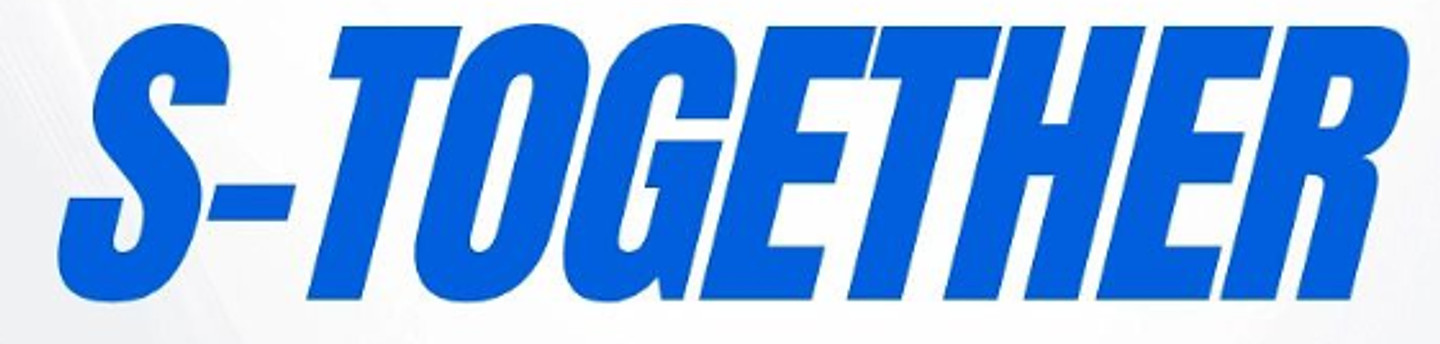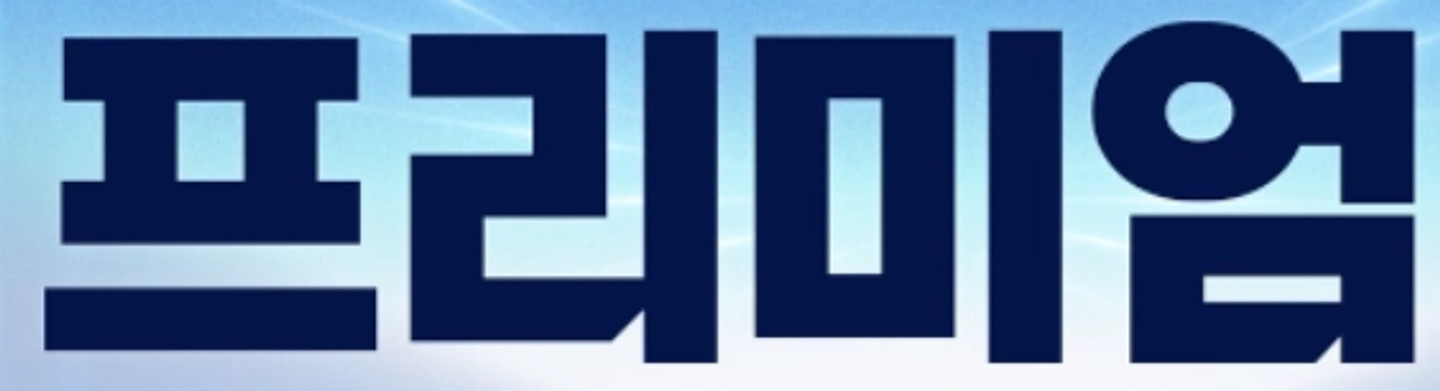
사천항공체 입니다.
요정재형 유튜브 폰트 아시는분~ㅜㅜ 프리텐다드랑 비슷한데 얄쌍하거든요. 진짜 다뒤져도 못찾았어요... 아시는분 ㅠㅠㅠㅠㅠㅠㅠㅠㅠㅠ꼭좀 답변 남겨주시면 감사드리겠습니다
아이폰 카카오톡에 쓰던 폰트인데 찾아주세요 ㅠ 오른쪽은 카톡 제목이라 좀 굵게 보이고, 원래는 왼쪽처럼 보입니다! 하트가 저런 게 특징인데 비슷한 것들만 보이고 못 찾겠어요 ㅠㅠ 몇 년 전에 해두었다가 얼ㅁ ㅏ전 아이폰 ios 업뎃했더니 갑자기 초기화가 돼버렸어요